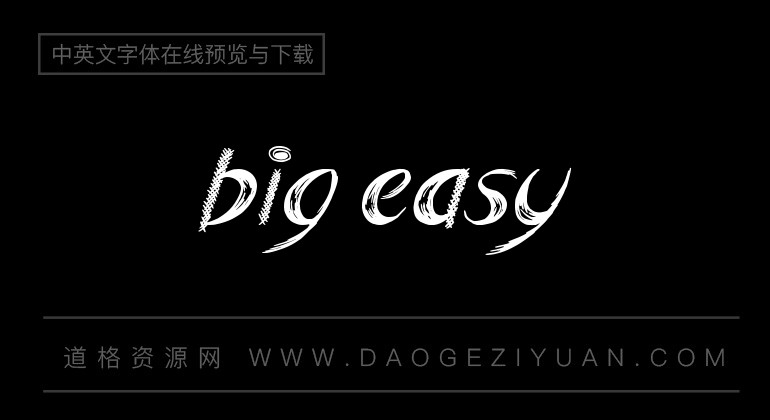
Big Easy
Big Easy 是一款极具视觉冲击力的英文字体,它的字形设计灵感来源于拉丁文字、欧洲文字以及美国招牌字体。Big Easy 的字体特点是细节精致、色彩丰富、曲线优美,在字体设计上有着独特的风格。它具有极强的可读性,在文字排版上也有着极佳的效果,适用于多种不同的印刷和屏幕应用。
Big Easy是一款非常不错的手写艺术字体,具有很好的视觉感,适合于文化类的宣传设计、商业类品牌的广告和产品包装设计以及个性化文字排版等较多场景。